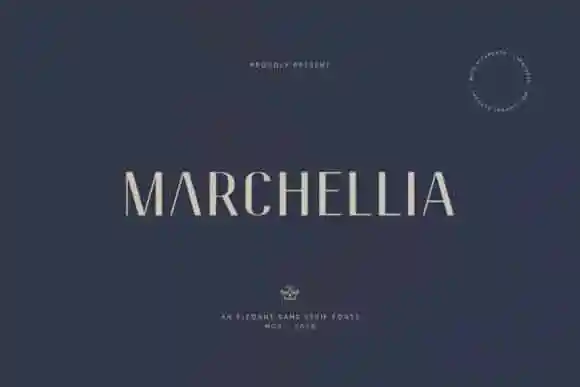
Marchellia Sans Serif Font – Fonte Grátis
Marchellia Sans Serif Font
Marchellia Sans Serif é uma fonte de tipo sem serif que se destaca por sua versatilidade. Esta tipografia minimalista e autêntica está projetada para funcionar igualmente bem em grandes e pequenos tamanhos, tornando-se uma escolha ideal para designers digitais. Suas linhas simples e alegres são perfeitas para complementar um leque vasto de projetos, fazendo com que eles se destacuem e se destaquem na web ou em qualquer outro meio digital. Seja você criatividade ou projeto, Marchellia Sans Serif é uma opção perfeita para dar uma nova dimensão aos seus ideais inovadores. Sua simplicidade permite que ela combine facilmente com outros recursos gráficos e ofereça um toque único a qualquer layout de site ou aplicativo digital. Descubra como Marchellia Sans Serif pode tornar suas criações em desfiles digitais mais atrativos e distintivos.